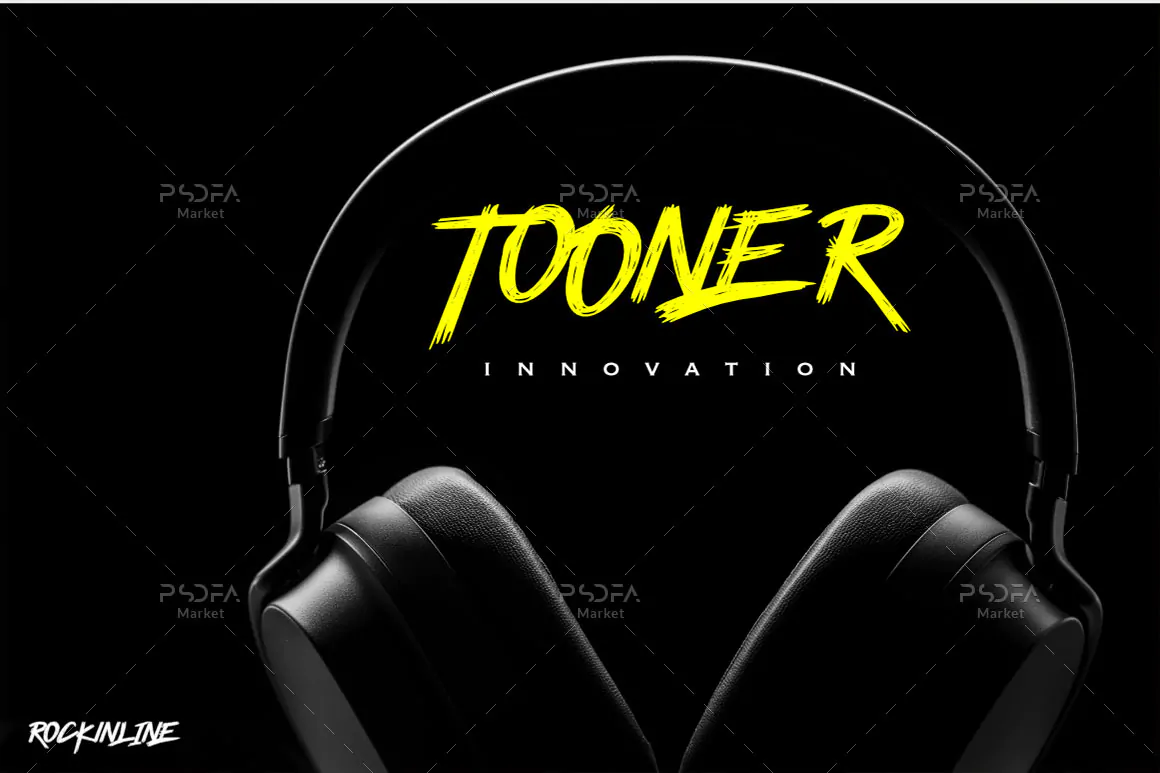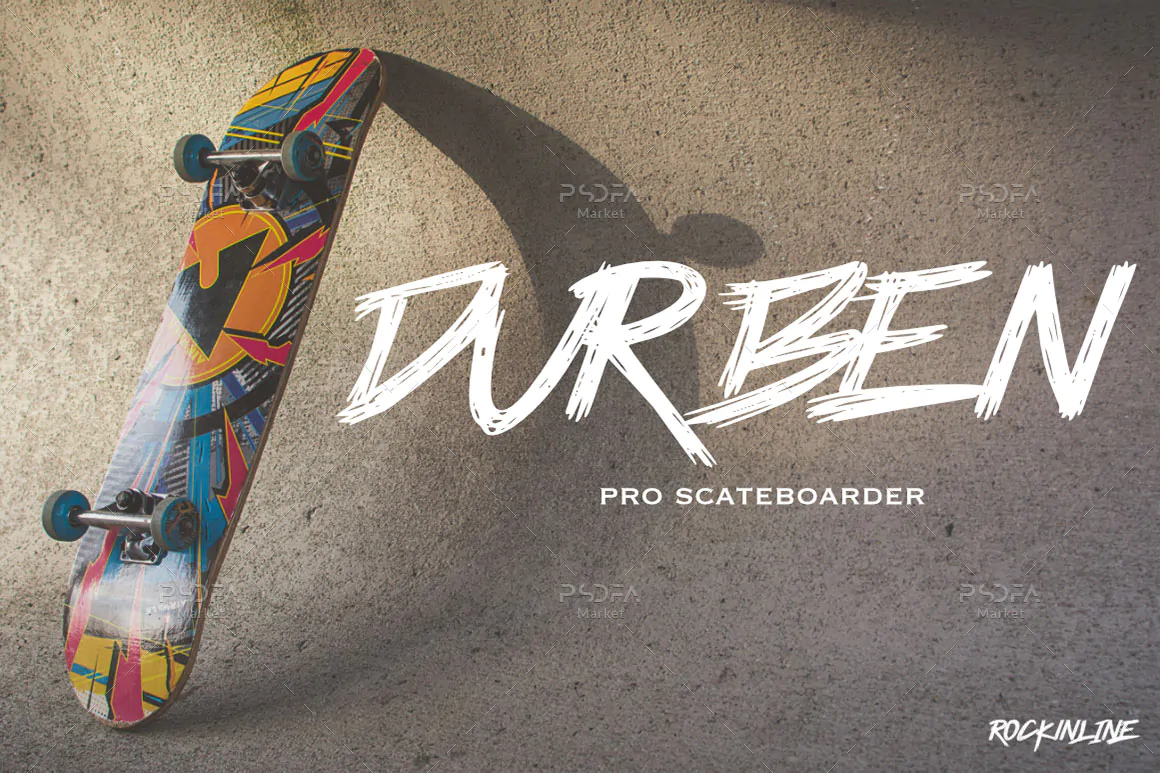
براش فونت انگلیسی Rockinline
براش فونت انگلیسی
براش فونت انگلیسی Rockinline یک قلم نمایشی فوق العاده زیبا است که مناسب جهت استفاده در نرم افزارهای گرافیکی مختلف میباشد. این فونت زیبا با وزن معمولی طراحی شده است که میتوانید از آن در طراحی انواع پوستر، بنر، بسته بندی محصولات، کارت ویزیت، تراکت و … استفاده کنید.
- وزن: Regular